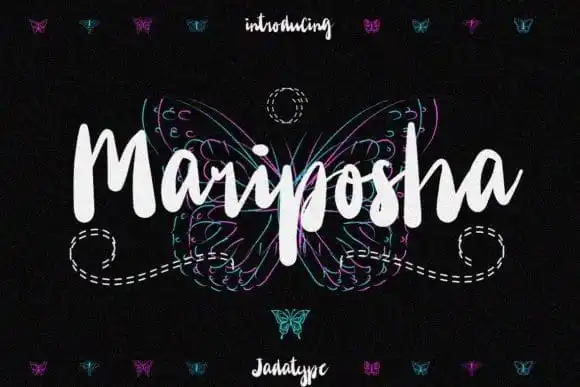
Mariposha Script Font – Fonte Grátis
Mariposha Script Font
A Mariposha Script Font é uma fonte criada pela jadatype que apresenta a personalidade descontraída e delicada de um traçado manual. Esta fonte traz a sensação fresca e fluida de uma escrita feita com um pincel, mantendo todas as nuances do processo artesanal em cada letra, desde os arranhamentos finos até às linhas suaves e levemente desiguais. A jadatype cuidadosamente ajustou e aperfeiçoou esta font para garantir que você possa utilizar com total confiança, obtendo resultados limpos e bem equilibrados. Perfeita para adicionar um toque de personalidade ao seu próximo projeto gráfico ou design de arte digital, a Mariposha Script Font é uma escolha inteligente para criar designs únicos e emocionantes.